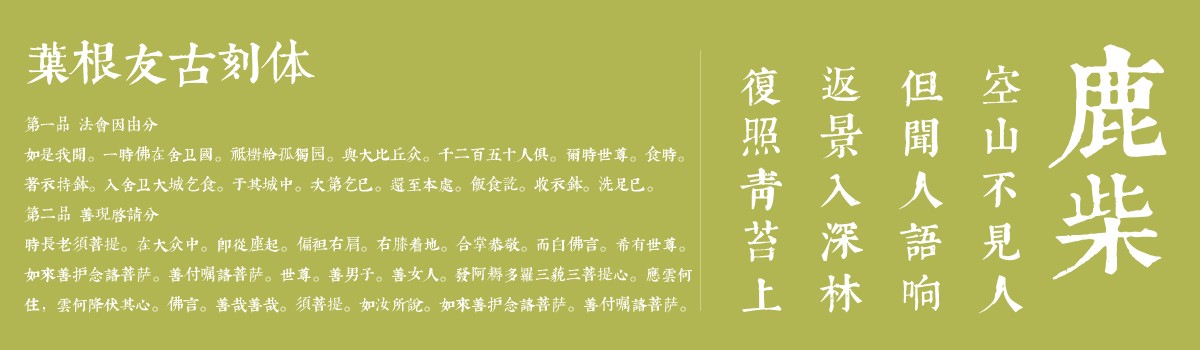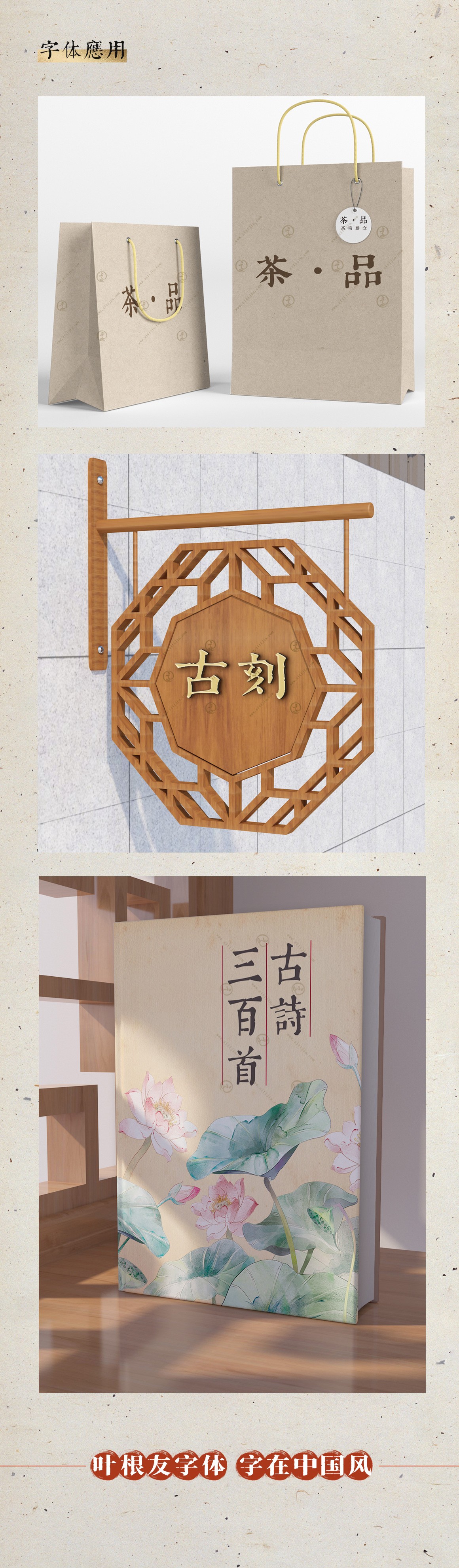
叶根友古刻体
字体介绍
叶根友古刻体是一款具有古意的书法字体,整个字形融合了这个书法的一种古体韵味,点横与捺都在书写着不同汉字的传奇色彩,是特别具有中国风的书法字体。叶根友古刻体,一种返璞归真的脚步在世间凝固,反过头去看看以前的字体,感觉是美好的,也是恋旧的一种情结,这款字体就是利用传统与现代的笔形结构进行设计的古刻字体,风格优雅而不失古风艺术。适合标题用字或者追求个性感觉的海报设计应用,现开放个人版下载,商业用途请购买正版授权,侵权必究!